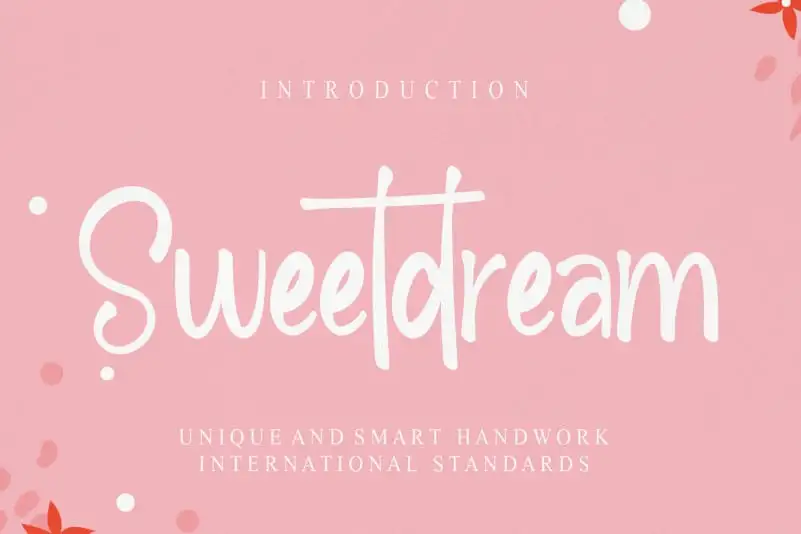
Sweetdream Brush Font – Fonte Grátis
Sweetdream Brush Font
A fonte ‘Sweetdream Brush Font’ é uma escolha perfeita para qualquer designer que busca uma escrita handwritten sofisticada e envolvente. Criada pelo talentoso Designer: creativeletter, esta fonte oferece um toque de serenidade e criatividade sem igual em suas linhas fluidas e delicadas. Os traços suaves da Sweetdream Brush Font proporcionam um estilo único que combina charme pessoal com uma leveza na escrita, tornando-a ideal para projetos como cards de casamento ou cartões de aniversário. Não apenas é uma opção versátil e criativa, mas também oferece a conveniência de ser parte da categoria Handwritten Fonts. Inspirada em traços suaves que evocam um sonho de sono, esta fonte reflete o conceito original “DETAILS special creative products for you” com perfeição, elevando seus projetos ao próximo nível.